Canvaで数字フォントを探してるけど、どれがオシャレに見える?
フォント選びで、デザインの印象がガラッと変わるよね。
数字のフォントひとつで、洗練されたデザインにも、野暮ったいデザインにもなってしまう。
合わないフォントを使うと、せっかくのデザインも台無しに…。
でも、適切なフォントを選べば、一気にプロっぽく仕上がるんです!
そこで今回は、Canvaで無料で使えるおしゃれな数字フォントおすすめ7選を紹介します!
- デザインに合う数字フォントの選び方
- Canvaで使えるおすすめフォント7選
- フォントを活かしたデザインのコツ
Canva無料で使えるおしゃれな数字フォントおすすめ7選
Canvaには、無料で使えるおしゃれな数字フォントが豊富にそろっています。
特に、数字デザインにこだわりたい方のために、洗練されたフォントを厳選しました。
- Montserrat(モダンでスタイリッシュ)
- Lato(シンプル&使いやすい)
- Bebas Neue(太字で目立つ見出し向き)
- Playfair Display(エレガントで上品な雰囲気)
- Raleway(洗練された細身のデザイン)
- Oswald(力強く、ポスター向き)
- Dancing Script(手書き風でかわいい)
これらのフォントは、無料で使える上に、さまざまなデザインに応用可能です。
それでは、各フォントの特徴を詳しく見ていきましょう。
Montserrat(モダンでスタイリッシュ)
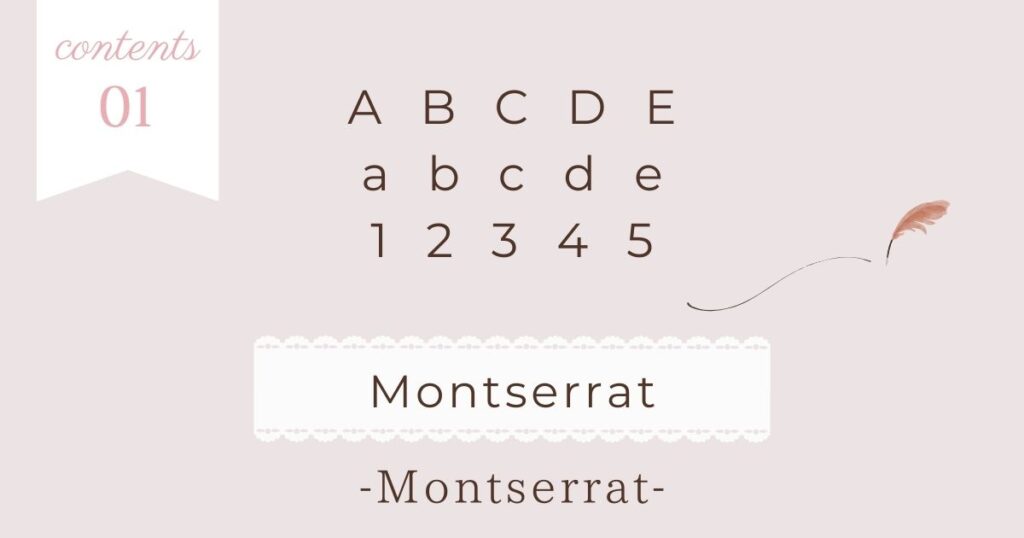
Montserratは、モダンで洗練された印象を与えるフォントです。
視認性が高く、太字にすると力強さが増すため、ポスターやプレゼン資料にも最適。
- モダンなデザインにマッチ
- 太字でも細字でもバランスが良い
- タイトルや見出しに適している
すっきりとしたフォルムが特徴で、シンプルなデザインにぴったりです。
Lato(シンプル&使いやすい)
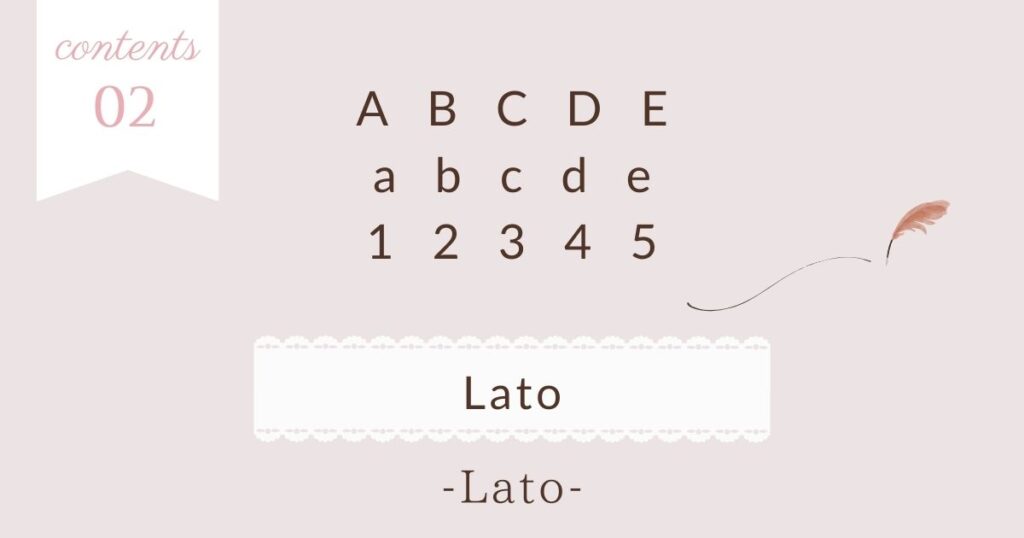
Latoは、クセのないシンプルなデザインで、どんなデザインにもなじみます。
細身のラインが上品な印象を与え、ナチュラルな雰囲気のデザインにも最適です。
- シンプルで読みやすい
- ナチュラルな雰囲気にも合う
- 見出しや本文どちらにも使いやすい
洗練されたフォントを求めるなら、Latoは間違いありません。
Bebas Neue(太字で目立つ見出し向き)
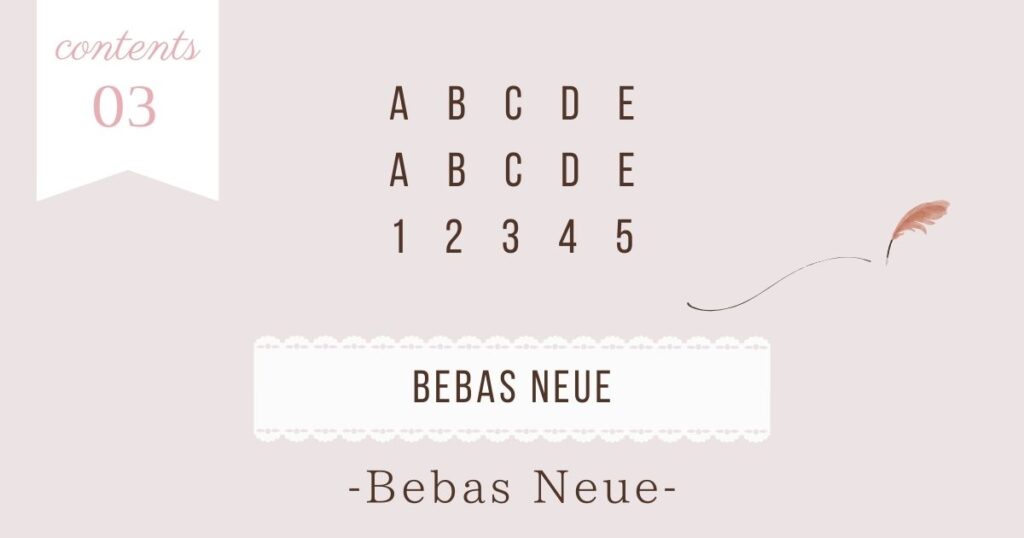
Bebas Neueは、太字でインパクトのあるフォント。
特に、ポスターや見出しなど、目を引くデザインに最適です。
- 太字で視認性抜群
- ポスターやタイトルに向いている
- シンプルながら力強いデザイン
メリハリのあるデザインを作りたいときにおすすめです。
Playfair Display(エレガントで上品な雰囲気)
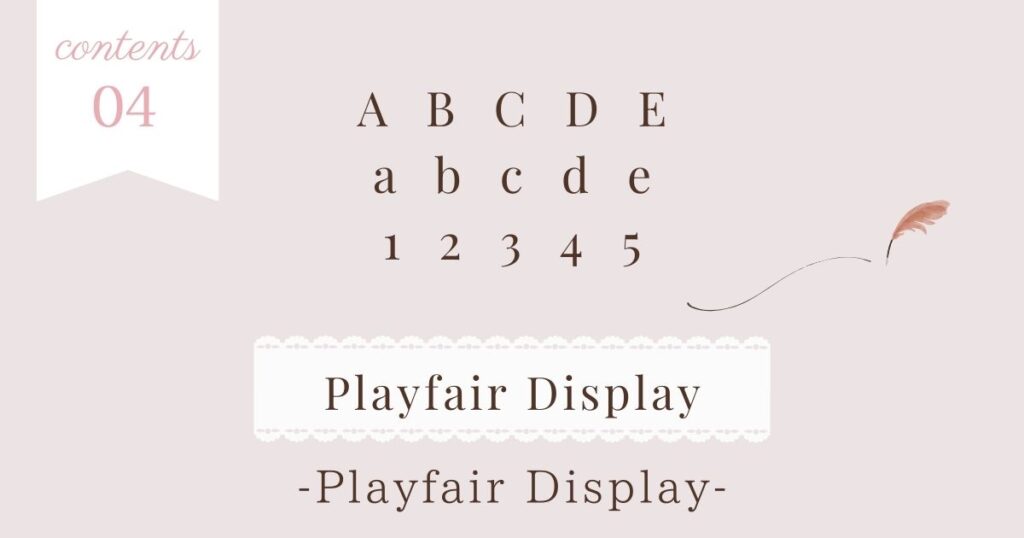
Playfair Displayは、エレガントでクラシックな印象のフォント。
細字で洗練されたデザインにぴったりで、上品な雰囲気を演出します。
- エレガントで上品なデザイン向き
- 女性向けデザインに最適
- 高級感を演出できる
洗練されたデザインを目指すなら、Playfair Displayが最適です。
フォント選びでデザインの印象が大きく変わります!
Raleway(洗練された細身のデザイン)
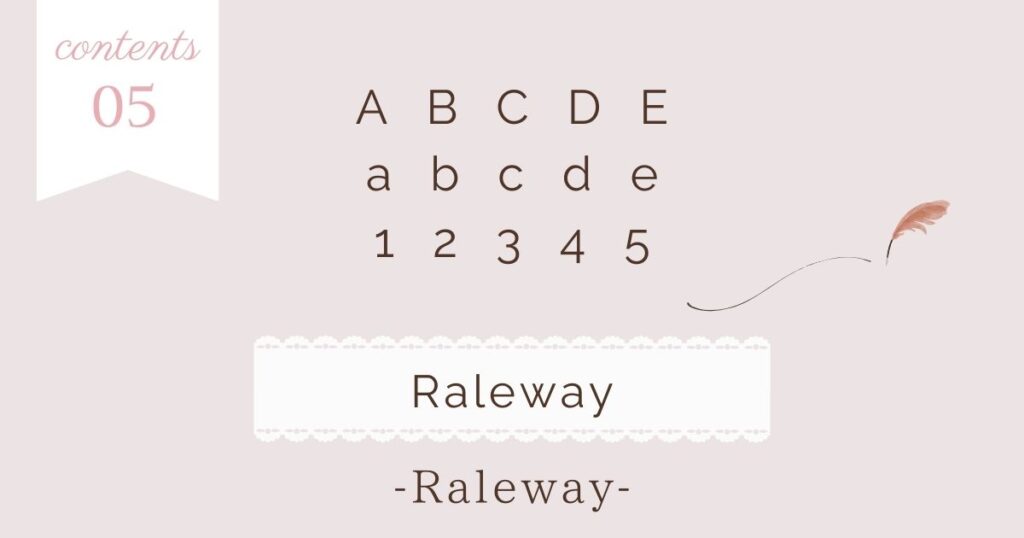
Ralewayは、細身でモダンなデザインが特徴のフォント。
シンプルながらもスタイリッシュで、ミニマルなデザインに最適です。
- 細身のラインで洗練された印象
- 高級感のあるデザインにマッチ
- ロゴやブランドデザインにも適用可能
ミニマルで洗練されたデザインを作りたい方におすすめのフォントです。
Oswald(力強く、ポスター向き)
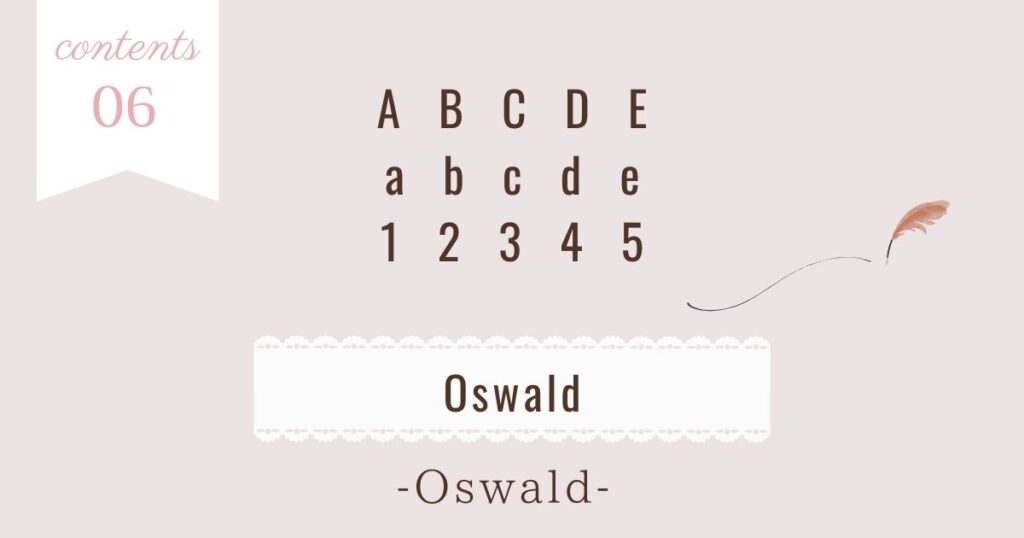
Oswaldは、太字で存在感のあるフォント。
ポスターや広告のデザインで目立たせたいときに最適です。
- 太字でインパクトがある
- タイトルや見出しに最適
- ポスターや広告向けデザインにピッタリ
力強いデザインに仕上げたい場合は、Oswaldを選ぶと良いでしょう。
Dancing Script(手書き風でかわいい)
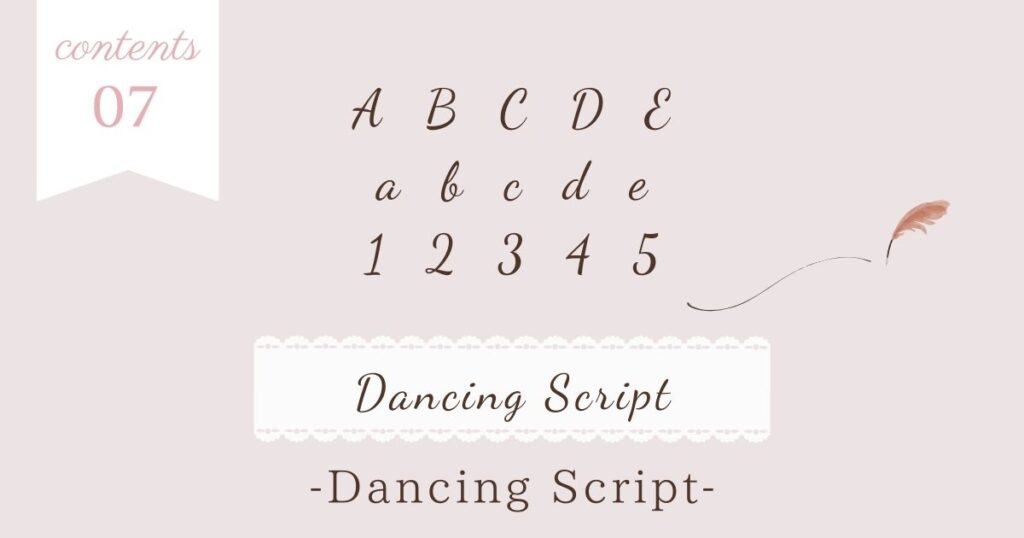
Dancing Scriptは、手書き風で可愛らしい雰囲気のフォント。
カジュアルなデザインや女性向けのデザインにぴったりです。
- 手書き風の柔らかい印象
- カジュアルで親しみやすいデザイン向き
- カードやSNS投稿にも最適
かわいい雰囲気のデザインを作りたいなら、Dancing Scriptがおすすめです。
無料でも優秀なフォントがたくさんありますね!
デザインに合う数字フォントの選び方【初心者向け】
おしゃれな数字フォントを選ぶ際は、デザインの目的に合ったものを選ぶことが重要です。
フォントの選び方を知っておくと、統一感のあるデザインが作りやすくなりますよね。
適切なフォントを選ぶことで、伝えたいメッセージがより効果的に伝わります。
ここから、数字フォントの選び方を具体的に解説します。
見やすさを重視するフォントの選び方
フォント選びで最も大切なのは「見やすさ」です。
特に数字フォントは、読み間違いが発生しやすいため、はっきりしたデザインを選びましょう。
- シンプルなサンセリフフォント(例:Montserrat, Lato)
- 適度な太さがあるフォント(例:Raleway, Oswald)
- 字間が詰まりすぎていないもの
フォントの可読性を意識することで、伝わりやすいデザインが作れます。
ブランドやデザインテーマに合わせるポイント
デザインのテーマやブランドイメージに合わせたフォント選びも重要です。
例えば、高級感を出したいなら「Playfair Display」、ポップなデザインには「Bebas Neue」など、雰囲気に合うフォントを選びましょう。
- 高級感:Playfair Display、Raleway
- モダン:Montserrat、Lato
- カジュアル・ポップ:Bebas Neue、Dancing Script
フォントの個性を活かすことで、ブランドの印象を強めることができます。
フォントの太さや間隔の調整方法
フォントの太さや字間を適切に調整すると、デザインのバランスが整います。
Canvaでは「文字間(カーニング)」や「行間(ラインハイト)」を調整できるので、読みやすさを意識しましょう。
- 太さを調整して強調したい部分を目立たせる
- 文字間を広げるとスタイリッシュな印象に
- 行間を詰めるとまとまりのあるデザインに
フォントの配置や調整を意識するだけで、プロっぽいデザインに仕上がりますよ。
フォントの選び方次第で、デザインの印象が大きく変わりますね!
Canvaで数字フォントを活用したおしゃれなデザイン事例3選
おしゃれな数字フォントを使うことで、デザインの印象が大きく変わります。
実際にCanvaを活用して、どのようなデザインが作れるのか具体例を見てみましょう。
デザインの目的に応じて、最適なフォントを選ぶことが大切です。
それでは、具体的な活用事例を見ていきましょう。
ポスターやチラシでの活用例
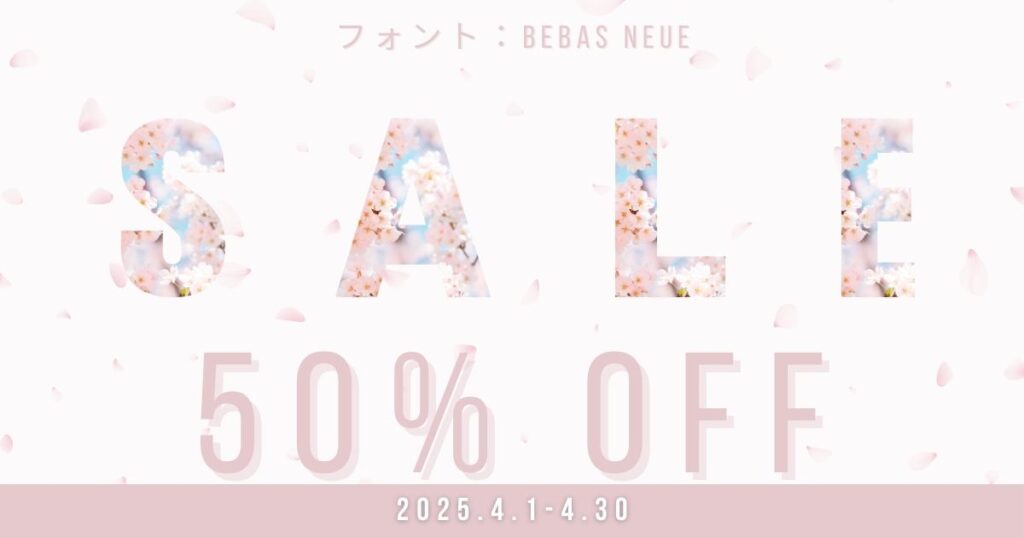
数字フォントは、ポスターやチラシのデザインで特に重要です。
例えば、イベント告知ポスターでは、大きな数字を使って日付や料金を目立たせることで視認性が向上します。
- 見出し向け: Bebas Neue(太字でインパクト大)
- サブテキスト向け: Montserrat(モダンで読みやすい)
- 手書き風アクセント: Dancing Script(親しみやすい雰囲気)
特に「Bebas Neue」は、ポスターのタイトルや大きな数字部分に適しています。
SNS投稿画像での使い方
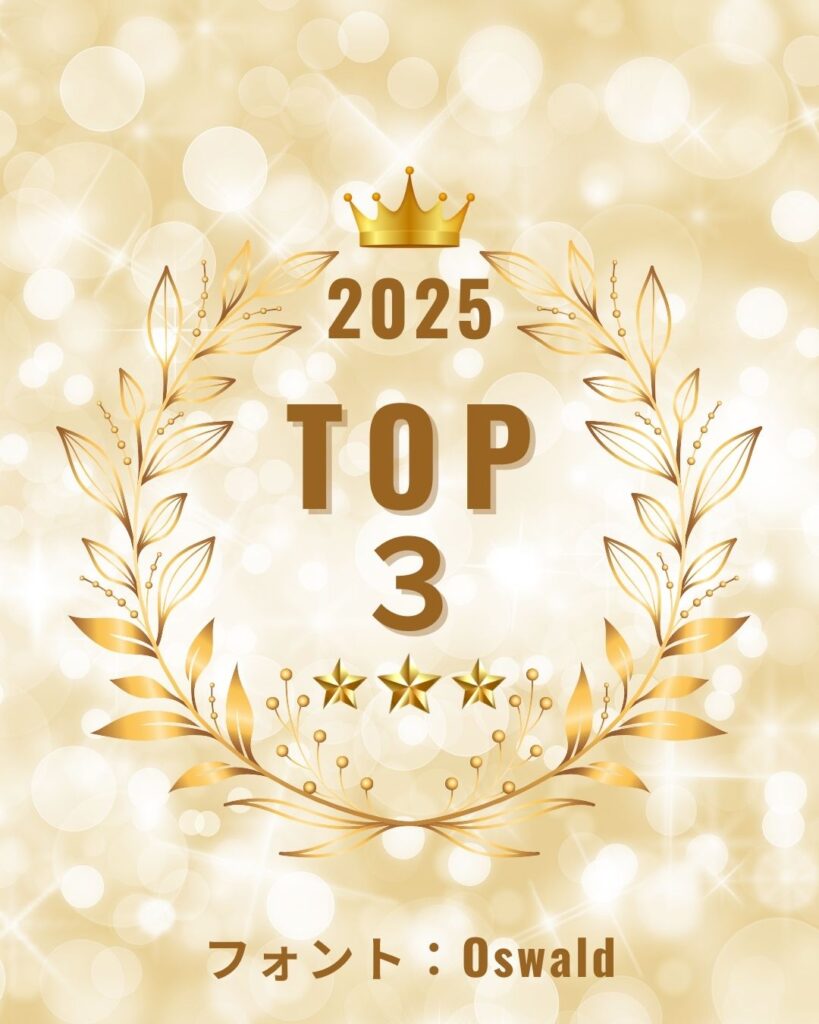
InstagramやTwitterなどのSNS投稿では、数字フォントを使って情報を強調できます。
例えば、セール情報やランキングを視覚的にわかりやすくするために、印象的な数字フォントを使用しましょう。
- ランキング投稿: Oswald(力強くて目を引く)
- セール情報: Playfair Display(高級感のあるデザイン向き)
- カジュアルな投稿: Lato(シンプルで柔らかい雰囲気)
数字を強調することで、投稿の視認性が上がり、エンゲージメントの向上にもつながります。
ブログやプレゼン資料での応用
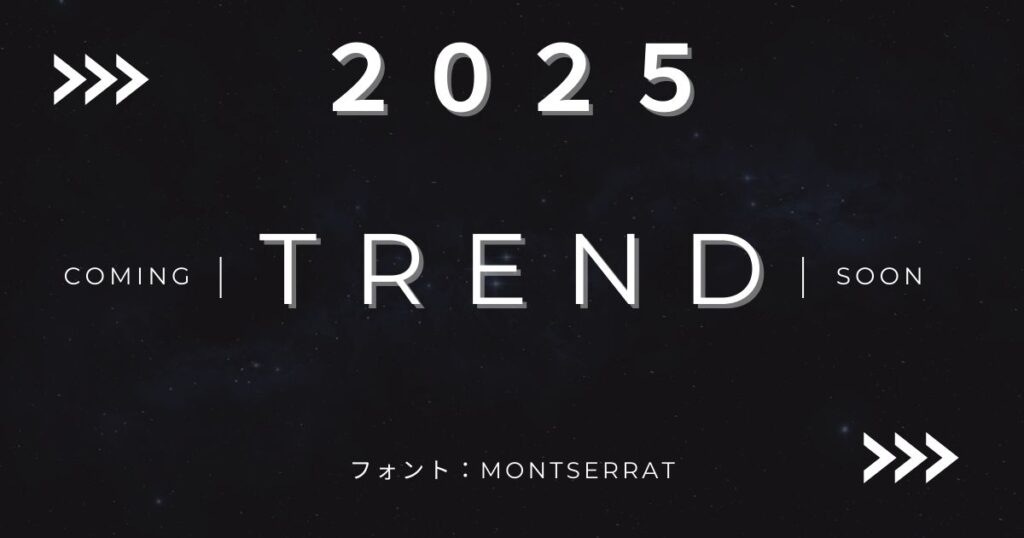
ブログ記事やプレゼン資料でも、数字フォントを効果的に使うことで、情報が伝わりやすくなります。
特に、統計データやランキング、見出しのデザインにこだわることで、より魅力的な資料を作ることができます。
- 統計データの強調: Raleway(細身で上品な印象)
- タイトルや見出し: Montserrat(モダンで読みやすい)
- 注釈や補足: Lato(視認性が高くナチュラル)
視覚的に整理されたフォントを使用すると、読者にとってわかりやすいコンテンツになります。
フォントを使い分けることで、デザインの質がぐっと上がりますね!
まとめ|Canvaで使えるおしゃれな数字フォント
今回は、Canvaで無料で使えるおしゃれな数字フォントと、その選び方・活用法について紹介しました。
- Canvaで無料で使えるおすすめの数字フォント7選
- フォント選びでデザインの印象が変わる理由
- ポスター・SNS・ブログなどの活用事例
フォント選びひとつで、デザインの印象は大きく変わります。
モダンな「Montserrat」、エレガントな「Playfair Display」、目立つ「Bebas Neue」など、目的に合わせて使い分けることで、より魅力的なデザインに仕上がりますよ!
数字フォントの選び方がわかったし、いろいろ試したくなった!
Canvaを活用して、おしゃれなデザインをどんどん作ってみてね!